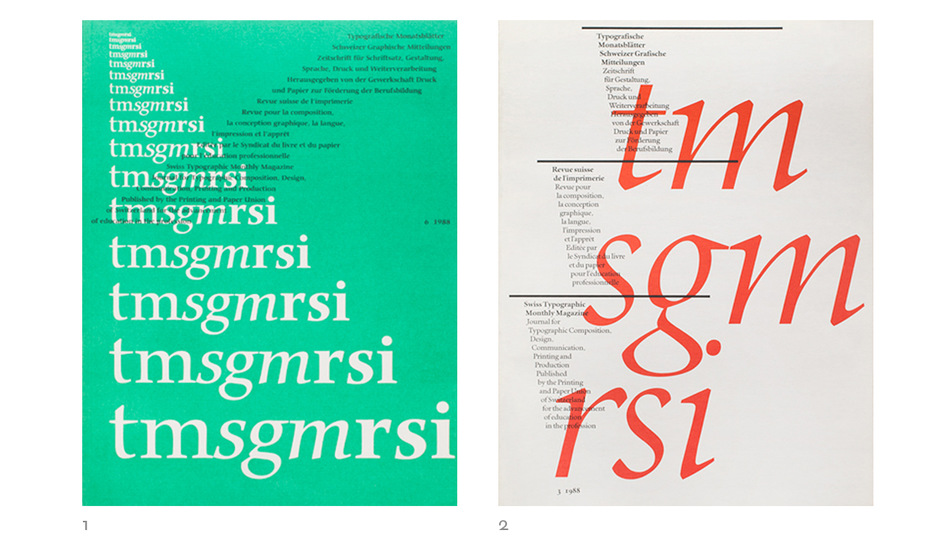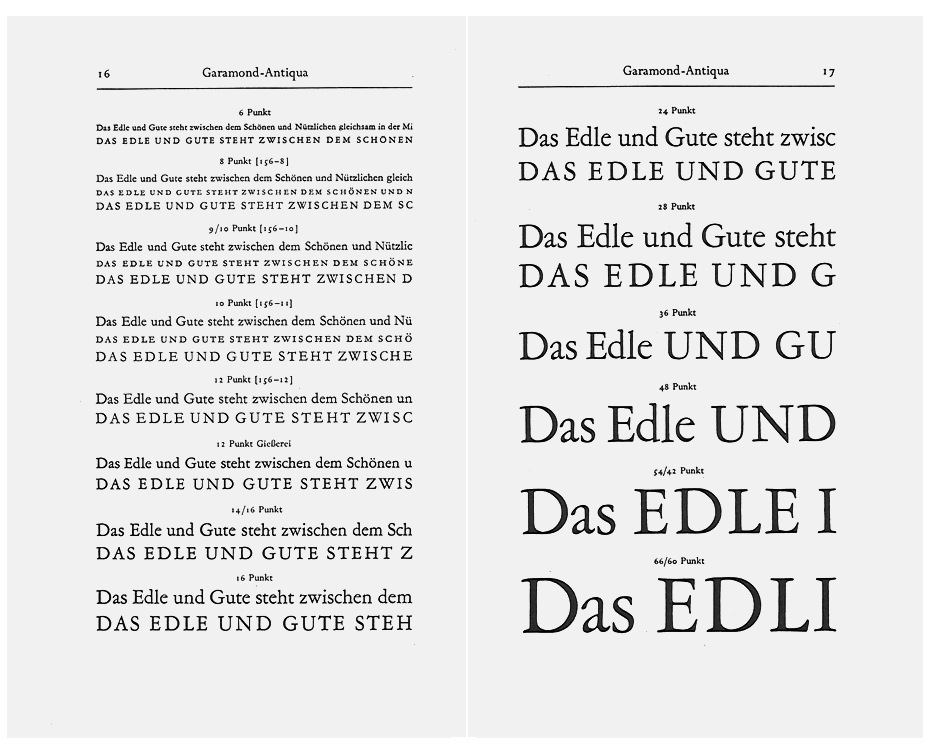
Макс Кафлиш и «идеальная книга»
ак­с Ка­фли­ш (* 25 ок­тя­бря 1916, Вин­тер­тур; † 3 мар­та 2004) не из­вест­ен рус­ско­му чи­та­те­лю в той ме­ре, в ка­кой этот швей­цар­ский ти­по­граф то­го за­слу­жи­ва­ет. Его со­вре­мен­ни­ку Яну Чи­холь­ду по­вез­ло боль­ше бла­го­да­ря пе­ре­ведён­но­му на рус­ский язык и из­дан­но­му «Об­ли­ку кни­ги» (М.: «Кни­га», 1980; М.: «Из­дал», 2008). Макс Ка­флиш прошёл впе­чат­ля­ю­щий про­фес­си­о­наль­ный путь: с 1932 по 1936 год он обу­чал­ся осно­вам руч­но­го на­бо­ра вме­сте с уже упо­мя­ну­тым Яном Чи­холь­дом и Имре Рай­не­ром, в го­ды вой­ны изу­чал ти­по­гра­фи­ку в Ба­зе­ле, по­сле по­чти два­дцать лет жиз­ни по­свя­тил ра­бо­те арт-ди­рек­то­ром в круп­ней­шем ­на тот мо­мент ев­ро­пей­ском из­да­тель­стве Benteli в Бер­не. Макс Ка­флиш стал из­ве­стен как пре­по­да­ва­тель и гла­ва де­пар­та­мен­та гра­фи­че­ско­го ди­зай­на в Учи­ли­ще ис­кусств и ремё­сел в Цю­ри­хе и в Тех­ни­че­ском по­ли­гра­фи­че­ском учи­ли­ще. Кро­ме это­го, Ка­флиш был кон­суль­тан­том по ти­по­гра­фи­ке в ком­па­ни­ях IBM и Adobe. Что­бы по­зна­ко­мить вас с этим уни­каль­ным ти­по­гра­фом, мы пе­ре­ве­ли эс­се Гер­ма­на Цап­фа о Мак­се Ка­фли­ше из сбор­ни­ка эс­се и пуб­ли­ка­ций о нём Typographia practica (1988). От ре­дак­ции
Макс Ка­флиш — ти­по­граф. Ти­по­граф ста­рой шко­лы. Нуж­на ли эта про­фес­сия в на­ше вре­мя, ко­гда ком­пью­тер­ы всё стре­ми­тель­нее вы­тес­ня­ют на­вы­ки ква­ли­фи­ци­ро­ван­но­го ти­по­гра­фа и ко­гда про­из­вод­ство пе­чат­ной кни­ги сто­ит пе­ред опас­но­стью ис­чез­но­ве­ния?
Ко­неч­но, кни­гу мож­но со­здать и без ти­по­гра­фа, как и ти­по­вое зда­ние мож­но по­стро­ить без ар­хи­тек­то­ра. Но ра­зум­но ли это? Функ­ция ти­по­гра­фа по су­ти и есть ра­бо­та ар­хи­тек­то­ра. Ти­по­граф, как и ар­хи­тек­тор, сво­и­ми ра­бо­та­ми не дол­жен пре­зен­то­вать са­мо­го се­бя. Он лишь пла­ни­ру­ет, про­ра­ба­ты­ва­ет и про­ду­мы­ва­ет оп­ти­маль­ное при­ме­не­ние как тех­ни­че­ских, так и эко­но­ми­че­ских средств для по­лу­че­ния хо­ро­шей кни­ги.
Но что та­кое хо­ро­шая кни­га? Су­ще­ству­ет ли во­об­ще иде­аль­ная кни­га, о ко­то­рой на ру­бе­же двух ве­ков так меч­тал Коб­ден-Сан­дер­сон? На прак­ти­ке мы по­сто­ян­но стал­ки­ва­ем­ся с ком­про­мис­са­ми, на­чи­ная с фи­нан­со­вых огра­ни­че­ний из­да­те­лем и за­кан­чи­вая со­блю­де­ни­ем норм про­из­вод­ства. С по­доб­ны­ми про­бле­ма­ми стал­ки­ва­лись и рань­ше. Оши­боч­но счи­тать, буд­то со­вре­мен­ные ди­зай­не­ры, ко­то­рых пе­ре­пол­ня­ют твор­че­ские идеи, име­ют не­огра­ни­чен­ную сво­бо­ду.
Мы гре­зим о без­упреч­ной, иде­аль­но вы­стро­ен­ной кни­ге. Но что про­ис­хо­дит в дей­стви­тель­но­сти? В про­цес­се про­из­вод­ства, как пра­ви­ло, по­яв­ля­ют­ся раз­лич­но­го ро­да пре­пят­стви­я­: не­вни­ма­тель­ность при на­бо­ре или пе­ча­ти, ошиб­ки тех­ни­ки или не­пред­ви­ден­ные слож­но­сти. По­это­му очень ред­ко уда­ёт­ся при­бли­зить­ся к це­ли — иде­аль­ной кни­ге. За­ме­тим сра­зу, что взгляд Мак­са Ка­фли­ша на кни­гу ни­чуть не упро­ща­ет де­ла. Он ви­дит та­кие ме­ло­чи, на ко­то­рые обыч­ный че­ло­век и не об­ра­ща­ет вни­ма­ния.
Спеш­ка, при­су­щая на­ше­му вре­ме­ни, ещё боль­ше ме­ша­ет со­зда­нию со­вер­шен­ной кни­ги. И толь­ко не­мно­гим ди­зай­не­рам во­пре­ки всем труд­но­стям уда­ёт­ся до­стичь этой це­ли — со­здать кни­гу, ко­то­рая бы­ла бы чи­та­бель­на, ор­га­нич­но оформ­ле­на и вос­тре­бо­ва­на. На­ше се­го­дняш­нее пред­став­ле­ние о пе­чат­ных кни­гах для биб­лио­фи­лов силь­но от­ли­ча­ет­ся от пред­став­ле­ний Уильяма Морриса и Коб­де­на-Сан­дер­со­на.
Макс Ка­флиш вы­сту­па­ет за удоб­ную и вос­тре­бо­ван­ную кни­гу, без изо­щрён­ных ти­по­гра­фи­че­ских приёмов. Он не от­но­сит­ся к по­чи­та­те­лям чи­холь­дов­ской шко­лы с её дог­ма­тич­ной ти­по­гра­фи­кой. В до­кла­де, опуб­ли­ко­ван­ном к 20-ле­тию осно­ва­ния Меж­ду­на­род­ной ас­со­ци­а­ции ти­по­гра­фов (ATypI) в 1977 го­ду, на стра­ни­це 29 мы чи­та­ем: «Во­прос, сле­ду­ет ли на­бо­ру быть сим­мет­рич­ным или аси­ммет­рич­ным, к сча­стью, по­те­рял свою ак­ту­аль­ность. Ти­по­гра­фи­ка не долж­на быть тра­ди­ци­он­ной или про­грес­сив­ной, она долж­на быть вы­стро­е­на та­ким об­ра­зом, что­бы про­стей­ши­ми и дей­ствен­ны­ми сред­ства­ми оп­ти­маль­но до­сти­гать по­став­лен­ной це­ли».
Ка­флиш из­бе­га­ет сте­риль­но­го и ча­сто бес­смыс­лен­но­го ис­поль­зо­ва­ния гро­теск­ных шриф­тов в оформ­ле­нии кни­ги. При­ве­дён­ные ни­же при­ме­ры от­ра­жа­ют его ма­стер­ство как в со­зда­нии кни­ги, так и в вир­ту­оз­ном об­ра­ще­нии с ти­по­гра­фи­че­ски­ми де­та­ля­ми. Его ра­бо­ты уз­на­ва­е­мы чи­та­те­ля­ми, ко­то­рые не за­ме­ча­ют (хо­тя они и не долж­ны), сколь­ко раз­мыш­ле­ний и опы­та за­ло­же­но в про­стую и убе­ди­тель­ную кон­струк­цию кни­ги. У Мак­са Ка­фли­ша нет ти­по­гра­фи­че­ских из­ли­шеств, так как они про­ти­во­ре­чат его кон­цеп­ции бе­реж­ли­во­го вы­бо­ра шриф­тов. Он не свя­зы­ва­ет ди­зайн сво­их книг с ка­кой-ли­бо идео­ло­ги­ей или шко­лой и не яв­ля­ет­ся по­сле­до­ва­те­лем так на­зы­ва­е­мой швей­цар­ской ти­по­гра­фи­ки. Его шриф­то­вые ре­ше­ния про­сты и убе­ди­тель­ны как в ра­бо­тах для раз­лич­ных из­да­тельств, так и в оформ­ле­нии Биб­лии. Они до­сти­га­ют­ся ло­гич­но по­стро­ен­ным ма­ке­том для каж­дой кни­ги и не за­ви­сят от то­го или ино­го сти­ля или на­ци­о­наль­ной тра­ди­ции.
Макс Ка­флиш пред­по­чи­та­ет удоб­ные в об­ра­ще­нии фор­ма­ты книг, при­ня­тые, на­при­мер, в из­да­тель­стве Hans Huber в Бер­не (ра­бо­ту над ко­то­ры­ми он дол­гие го­ды воз­глав­лял). Ему ин­те­рес­но из­да­ние школь­ных учеб­ни­ков с их раз­но­об­раз­ны­ми ти­по­гра­фи­че­ски­ми слож­но­стя­ми. Всё свое ма­стер­ство ти­по­граф вло­жил так­же в оформ­ле­ние Биб­лии, над ко­то­рой он ра­бо­тал для Вюр­тем­берг­ско­го цер­ков­но­го из­да­тель­ства.
Но где ле­жат ис­то­ки ма­стер­ства Мак­са Ка­фли­ша? Где он по­лу­чил опыт, ко­то­рый по­мо­га­ет ему при­ни­мать пра­виль­ные ре­ше­ния?
Макс Ка­флиш ро­дил­ся 25 ок­тя­бря 1916 го­да в Вин­тер­ту­ре (Швей­ца­рия). Он от­но­сит­ся к то­му по­ко­ле­нию, ко­то­рое в со­вер­шен­стве вла­де­ло ис­кус­ством руч­но­го на­бо­ра (что, к со­жа­ле­нию, не яв­ля­ет­ся в на­ше вре­мя са­мо со­бой ра­зу­ме­ю­щим­ся). Эти че­ты­ре го­да, с 1932 по 1936-й он про­вёл в ти­по­гра­фии Studer-Schläpfer в Хор­ге­не под Цю­ри­хом. За­тем Ка­флиш про­дол­жил обу­че­ние в учи­ли­ще ис­кусств в Цю­ри­хе (Zürcher Hochschule der Künste), а за­тем, с 1938 по 1941 год, в Ба­зе­ле, где он ра­бо­тал пер­вым на­бор­щи­ком ак­ци­дент­ной пе­чат­ной про­дук­ции в ти­по­гра­фии Бе­но Шва­бе (Benno Schwabe) и Бир­к­хой­зе­ра (Birkhäuser) и где од­но­вре­мен­но с ним тру­ди­лись Ян Чи­хольд и Имре Рай­нер (Imre Reiner). С 1943 по 1962 год он от­та­чи­вал ма­стер­ство в ти­по­гра­фии при из­да­тель­ском до­ме в Берн-Бюм­пли­це, где он был глав­ным ху­дож­ни­ком всей вы­пус­ка­е­мой про­дук­ции. На­ря­ду с этим он со­труд­ни­чал с не­сколь­ки­ми из­да­тель­ства­ми, та­ки­ми как Holbein в Ба­зе­ле, Francke und Herbert Lang в Бер­не. Па­рал­лель­но Макс Ка­флиш ра­бо­тал с го­су­дар­ствен­ным об­ра­зо­ва­тель­ным из­да­тель­ством в Бер­не и с из­да­тель­ством Artemis в Цю­ри­хе.
Сле­ду­ет упо­мя­нуть о его пре­по­да­ва­тель­ской де­я­тель­но­сти, ко­то­рая на­ча­лась в пе­ри­од Вто­рой ми­ро­вой вой­ны, в 1941–1942 го­дах, в Ба­зе­ле, в учи­ли­ще ис­кусств, и про­дол­жи­лась в 1962 го­ду в Ака­де­мии ис­кусств в Цю­ри­хе. Там Макс Ка­флиш был на­зна­чен ру­ко­во­ди­те­лем пре­по­да­ва­тель­ско­го со­ста­ва. На этот пе­ри­од (он ра­бо­тал до 1981 го­да) при­хо­дит­ся пла­ни­ро­ва­ние и оформ­ле­ние но­во­го зда­ния гра­фи­че­ско­го фа­куль­те­та. Свои пе­да­го­ги­че­ские ме­то­ди­ки Ка­фли­шу уда­лось опро­бо­вать и в Тех­ни­че­ском учи­ли­ще гра­фи­че­ской про­мыш­лен­но­сти (Technikerschule der grafischen Industrie Zürich, TGZ), где он про­ра­бо­тал с 1973 по 1978 год.
Меж­ду­на­род­ное при­зна­ние его кни­ги по­лу­чи­ли на кон­кур­сах луч­шей кни­ги Швей­ца­рии, За­пад­ной Гер­ма­нии, Аме­ри­ки и на меж­ду­на­род­ной вы­став­ке книж­но­го ис­кус­ства в Лейп­ци­ге (2 зо­ло­тые ме­да­ли, се­ре­бря­ная, пер­вая пре­мия «Зо­ло­тая бук­ва»). В осно­во­по­ла­га­ю­щем тру­де «Осно­вы ти­по­граф­ско­го на­бо­ра», ко­то­рый был опуб­ли­ко­ван в 1951 го­ду в еже­ме­сяч­ном жур­на­ле Typographische Monatsblätter (вып. I, 1951), Ка­флиш раз­би­ра­ет ти­по­гра­фи­че­ские ню­ан­сы. Этот труд всё еще ак­туа­лен и мо­жет слу­жить учеб­ным по­со­би­ем, не­смот­ря на то что от­но­сит­ся толь­ко к ме­тал­ли­че­ским шриф­там для руч­но­го на­бо­ра.
Об­шир­ные зна­ния Ка­фли­ша в об­ла­сти ти­по­граф­ской тех­ни­ки при­го­ди­лись ком­па­нии IBM — в 1962 го­ду комью­тер­ный ги­гант при­гла­сил ди­зай­не­ра за­нять­ся со­став­ле­ни­ем шриф­то­вой биб­лио­те­ки для на­бор­ных ма­шин IBM Composer. Поз­же, в 1965 го­ду, Ба­вар­ская шриф­то­ли­тей­ная ма­стер­ская во Франк­фур­те-на-Май­не при­влек­ла его в ка­че­стве кон­суль­тан­та по ти­по­гра­фи­ке. В их шриф­то­ли­тей­ном це­ху был от­лит шрифт Ка­фли­ша Columna (1955). Са­мые со­вре­мен­ные раз­ра­бот­ки то­же не оста­ва­лись без его вни­ма­ния: с 1972 го­да Ка­флиш тру­дил­ся кон­суль­тан­том ком­па­нии док­то­ра Ру­доль­фа Хел­ла, где от­ве­чал за все их шриф­то­вые на­прав­ле­ния.
Един­ствен­ный шрифт Мак­са Ка­фли­ша, са­мо­сто­я­тель­но им спро­ек­ти­ро­ван­ный, — URW Columna (пер­вая вер­сия бы­ла вы­пу­ще­на в 1955 го­ду). Это ак­ци­дент­ный шрифт для на­бо­ра круп­ных за­го­лов­ков. Его фор­мы, как не­труд­но за­ме­тить, вдох­нов­ле­ны рим­ским ка­пи­таль­ным пись­мом, од­на­ко это ка­са­ет­ся лишь про­пор­ций и ши­рин букв. Шрифт до­ста­точ­но не­кон­траст­ный, плот­ный, сла­бо мо­ду­ли­ро­ван­ный и с не­ожи­дан­ны­ми для его ком­плек­ции ко­рот­ки­ми во­лос­ны­ми за­сеч­ки­ми. Осо­бое вни­ма­ние при­вле­ка­ют эле­гант­ные циф­ры, ко­то­рые на­ри­со­ва­ны с под­лин­ным ар­ти­стиз­мом и в то ­же вре­мя с глу­бо­ким по­ни­ма­ни­ем тра­ди­ции.
Моя сов­мест­ная ра­бо­та с Мак­сом Ка­фли­шем на­ча­лась в Сток­голь­ме в 1964 го­ду, ко­гда там про­хо­дил один из звёзд­ных се­ми­на­ров Бро­ра Ца­хрис­со­на (Bror Zachrisson). Этот се­ми­нар мы про­во­ди­ли с Бе­ат­рис Уорд (Beatrice Warde), и он был по­свящён про­бле­мам фо­то­на­бо­ра. По про­ше­ствии не­сколь­ких лет Макс Ка­флиш на ба­зе «Ком­па­нии Хел­ла» смог ре­а­ли­зо­вать свои идеи, свя­зан­ные со шриф­то­вы­ми про­грам­ма­ми. Его но­вые гар­ни­ту­ры боль­ше не яв­ля­лись пря­мой пе­ре­ра­бот­кой ис­то­ри­че­ских шриф­тов или вос­со­зда­ни­ем гар­ни­тур по ста­рым чер­те­жам.
Ду­маю, Макс Ка­флиш был пер­вым, кто спо­соб­ство­вал по­яв­ле­нию ори­ги­наль­ных шриф­тов, со­здан­ных с по­мо­щью циф­ро­вой тех­ни­ки. В ре­зуль­та­те на­шей сов­мест­ной де­я­тель­но­сти по­яви­лись мои шриф­ты Marconi-Antiqua (1973, опуб­ли­ко­ван в 1976), Edison-Antiqua (1977), Vario (1982), Aurelia-Antiqua (1983).
Се­го­дня де­я­тель­ность Ка­фли­ша охва­ты­ва­ет сфе­ру но­вей­ших раз­ра­бо­ток в об­ла­сти циф­ро­вой тех­ни­ки, в том чис­ле сли­я­ние ком­пью­тер­ной гра­фи­ки со шриф­том, что яв­ля­ет­ся ло­ги­че­ским путём раз­ви­тия ти­по­гра­фи­ки в бу­ду­щем. Счаст­ли­вое сте­че­ние об­сто­я­тельств — иметь та­ко­го че­ло­ве­ка в по­мощ­ни­ках и со­вет­чи­ках по тех­ни­че­ским во­про­сам.
Макс Ка­флиш оста­ёт­ся ти­по­гра­фом, ко­то­ро­го мы мно­гие го­ды зна­ем и ко­то­рым вос­хи­ща­ем­ся. Он не на­зы­ва­ет се­бя ди­зай­не­ром в об­ла­сти ви­зу­аль­ных ком­му­ни­ка­ций. Он ди­зай­нер кни­ги, ти­по­граф в са­мом глу­бо­ком смыс­ле это­го сло­ва. И та­кие спе­ци­а­ли­сты нуж­ны сей­час и бу­дут нуж­ны в бу­ду­щем.
То­мас Джеймс Коб­ден-Сан­дер­сон (Thomas James Cobden-Sanderson; * 2 де­ка­бря 1840; † 7 сен­тя­бря 1922) — ан­глий­ский ху­дож­ник, ди­зай­нер кни­ги и пе­ре­плёт­чик, дея­тель­ность ко­то­ро­го бы­ла свя­за­на с Дви­же­ни­ем ис­кусств и ремё­сел. Был бли­зок к се­мье Уи­лья­ма Мор­ри­са, под его же вли­я­ни­ем за­нял­ся пе­ре­плёт­ным де­лом (в част­но­сти, из­го­тав­ли­вал пе­ре­плёты для книг мор­ри­сов­ско­го из­да­тель­ства Kelmscott Press).
Опре­де­ле­ние «Иде­аль­ная кни­га» — часть на­зва­ния эс­се Коб­де­на-Сан­дер­со­на, за­кон­чен­но­го им в 1900 го­ду. В этом эс­се он, как и Уи­льям Мор­рис, про­воз­гла­ша­ет са­мо­до­ста­точ­ность всех ча­стей кни­ги — ли­те­ра­тур­но­го со­дер­жа­ния, бу­ма­ги, пе­ре­плёта, ил­лю­стра­ций, спо­со­ба пе­ча­ти и ти­по­гра­фи­ки как та­ко­вой. Со­еди­не­ние этих ча­стей в пра­виль­ном по­ряд­ке и рит­ме Коб­ден-Сан­дер­сон и на­зы­вал иде­аль­ной кни­гой. Од­на­ко он пред­по­чи­тал опи­рать­ся на чи­стую ти­по­гра­фи­ку и, в от­ли­чие от Мор­ри­са, от­вер­гал зна­че­ние ил­лю­стра­ции и ор­на­мен­та в кни­ге.
Со­вре­мен­ная циф­ро­вая вер­сия гар­ни­ту­ры име­ет 4 тек­сто­вых на­чер­та­ния и 3 дис­плей­ных. — Прим. ред.
В но­вой вер­сии гар­ни­ту­ры Самнер Сто­ун, на­про­тив, до­ба­вил эти за­сеч­ки. — Прим. ред.
В со­вре­мен­ной вер­сии шриф­та эти фор­мы вы­не­се­ны в от­дель­ный сет Swash Italic. — Прим. ред.
Так­же вы­не­се­ны в сет Swash Italic. — Прим. ред.
Уи­льям Мор­рис (William Morris; *24 мар­та 1834; † 3 ок­тя­бря 1896) — ан­глий­ский по­эт, ху­дож­ник, из­да­тель, один из ли­де­ров Дви­же­ния ис­кусств и ремё­сел. В 1891 го­ду осно­вал из­да­тель­ство Kelmscott Press. Из­да­тель­ская и ти­по­гра­фи­че­ская док­три­ны бы­ли из­ло­же­ны им в «За­мет­ке по по­во­ду от­кры­тия из­да­тель­ства Kelmscott Press» (1895). Уи­льям Мор­рис вдох­нов­лял­ся кал­ли­гра­фи­ей (и счи­тал её точ­кой от­счёта для кни­го­пе­ча­та­ния) и сред­не­ве­ко­вы­ми ру­ко­пис­ны­ми кни­га­ми. Kelmscott Press вы­пус­ка­ло изящ­ные кни­ги, вы­зы­ва­ю­ще не­по­хо­жие на мас­со­вые из­да­тель­ские но­вин­ки то­го вре­ме­ни. Глав­ным из­да­тель­ским прин­ци­пом Мор­рис счи­тал со­вер­шен­ство всех со­став­ля­ю­щих кни­ги: шриф­та, бу­ма­ги (она долж­на бы­ла быть не­пре­мен­но руч­но­го ли­тья), чер­нил, вёрст­ки и от­тис­ка (руч­но­го). Ор­на­мент дол­жен был со­че­тать­ся с изящ­ным шриф­том в ду­хе шриф­тов ве­не­ци­ан­ских пе­чат­ни­ков, раз­во­рот кни­ги стро­ил­ся с бо­га­ты­ми по­ля­ми, осо­бое вни­ма­ние уде­ля­лось глу­би­не и объ­ём­но­сти от­тис­ка, а так­же пе­ре­плёту кни­ги.